1305名のデザイナーが選ぶ、本当に好きなフォントランキングTOP10
株式会社リブセンスが運営するデザイナー、クリエイター限定の競争入札型の転職サイト「デザイナードラフト」は、登録ユーザーにおける登録項目の集計結果として、「1305名のデザイナーが選ぶ、本当に好きなフォントランキングTOP10」を2018年12月27日に発表した。
現役デザイナーが選ぶ、好きなフォントランキング
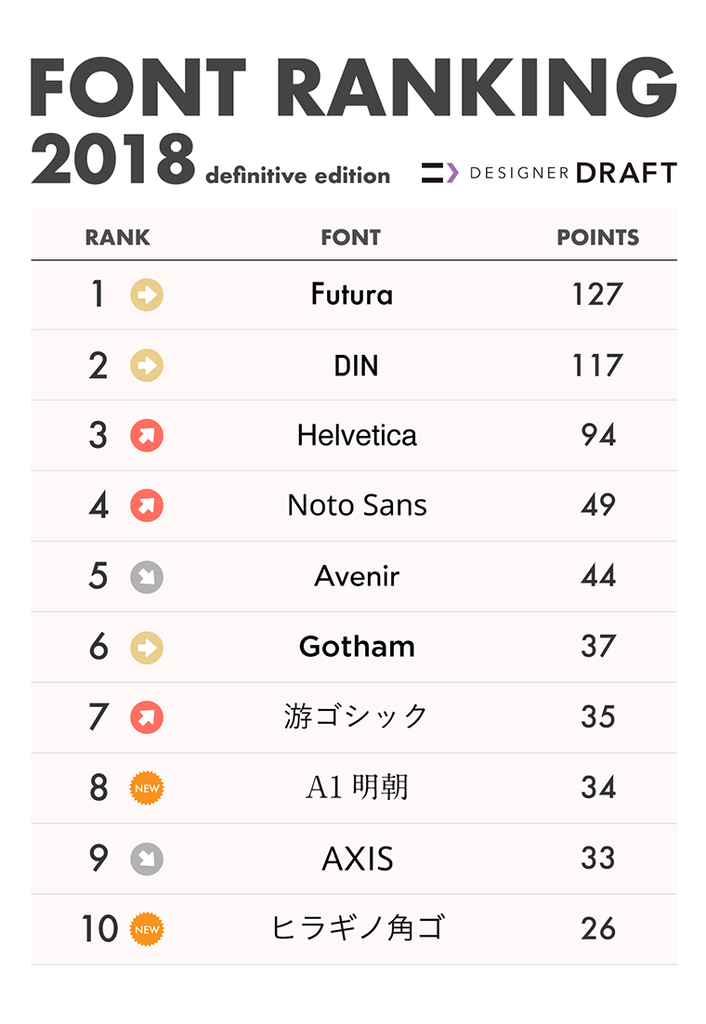
第1位 Futura
第2位 DIN
第3位 Helvetica
第4位 Noto Sans
第5位 Avenir / Avenir Next
第6位 Gotham
第7位 游ゴシック
第8位 A1明朝
第9位 AXIS
第10位 ヒラギノ角ゴ
ベスト3を欧文フォントが独占。ベスト30までみても欧文フォントが多数を占めている。
そんな中、4位にGoogleとAdobeが共同開発したオープンライセンスフォント・Noto Sans(源ノ角ゴシック)がランクインした。その他、日本語フォントとしては、游ゴシックや君の名は。でもおなじみのA1明朝などがランクイン。
ランキングは、デザイナードラフトの登録導線上に存在する「好きなフォント」という項目に入力されたフォントを集計したランキングとなる。
3位 Helvetica
デザイナーには馴染み深く、使用される頻度も高いフォント。PanasonicのロゴもHelvetica ですし、Microsoftも以前のロゴに採用されている。
2位 DIN
DINは、2020年東京オリンピック・パラリンピックの “TOKYO 2020” というのロゴに使われている。この1、2年の間はさらに頻繁に見かけることになりそう。
1位 Futura
Futuraのリリースは1927年。リリースから90年以上経った今でも、様々なフォントのベースとしても採用されているフォント。様々な所で利用されており、ブランドロゴですと、ルイ・ヴィトンやCalvin Klein、Red Bullなどの有名企業が採用されている。
4位以下のフォントランキング
6位のGothamに関しては、NetflixがGothamから独自フォントに移り変えてフォント利用料を削減したニュースが世間を騒がせたりと、業界内では何かと話題になっており、これからもフォント業界から目が話せない状況が続きそう。